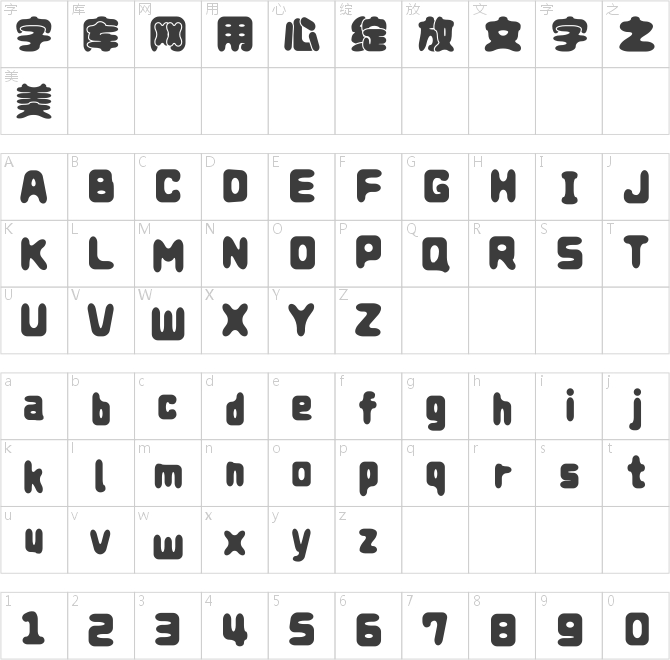
方正字迹-三余肥光体 详情页
方正字迹-三余肥光体
三余肥光体是一款萌胖可爱、柔软慵懒、稚趣十足的卡通类型美术字,字体负空间极小,整体饱满圆润,如同QQ糖/婴儿般柔软且富有弹性的笔划设定,融入部分笔划重叠的特征,营造出萌胖稚趣的氛围。设计之初想把肥光体设计成一款萌胖、柔软、可爱的字体,所以在笔划设定时,加入圆润粗厚的笔画特点,通过控制曲线线条的张力弧度,压缩字面负空间,部分笔划做重叠处理,在易识别的情况下,笔画间的灵活搭配更突显字体的柔软稚趣。 适用于海报招贴,漫画绘本、包装产品等周边领域。